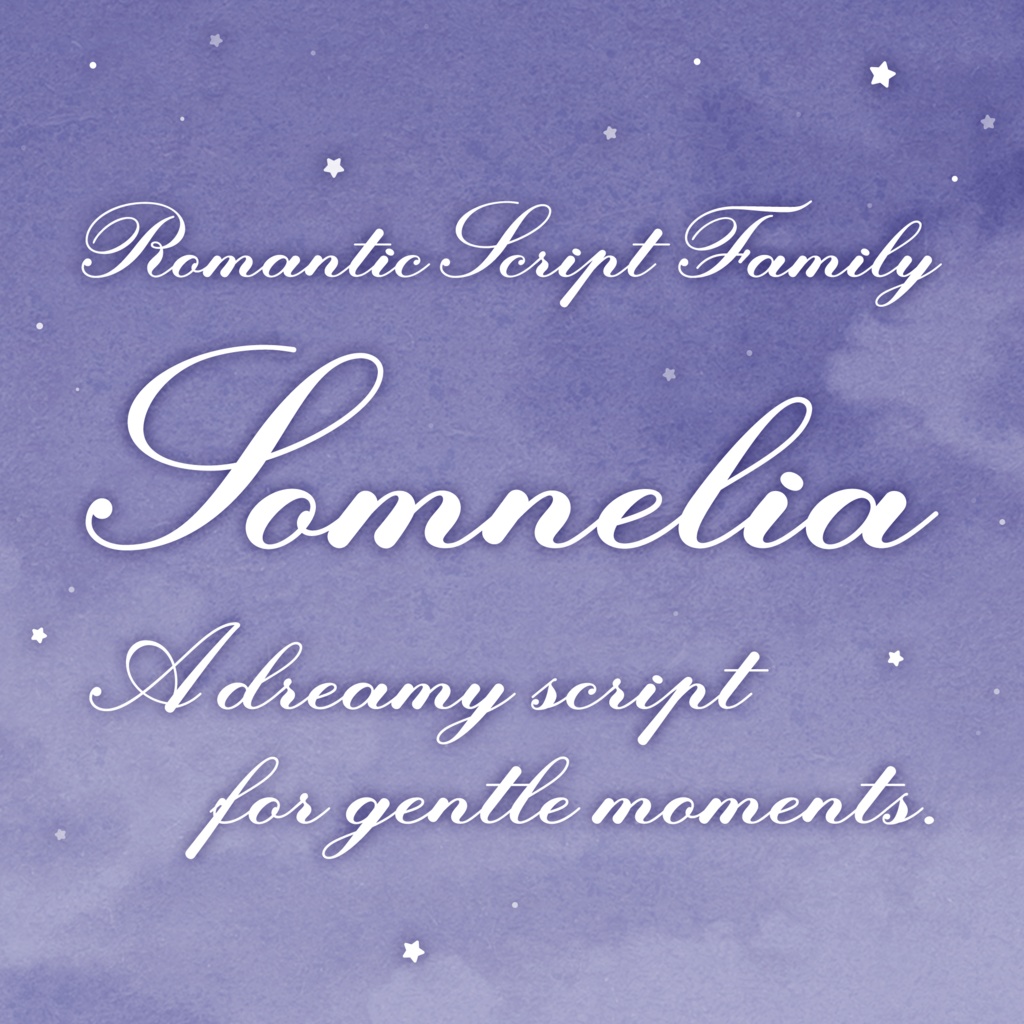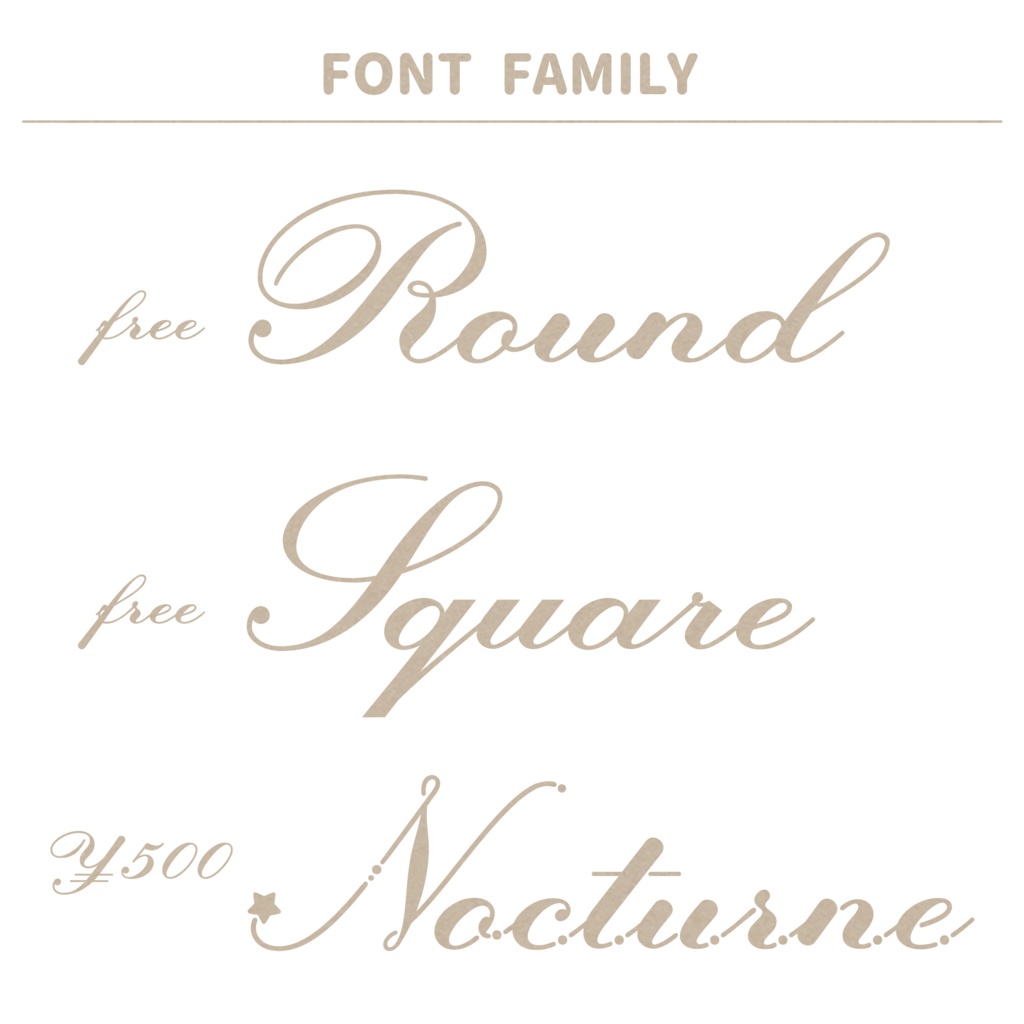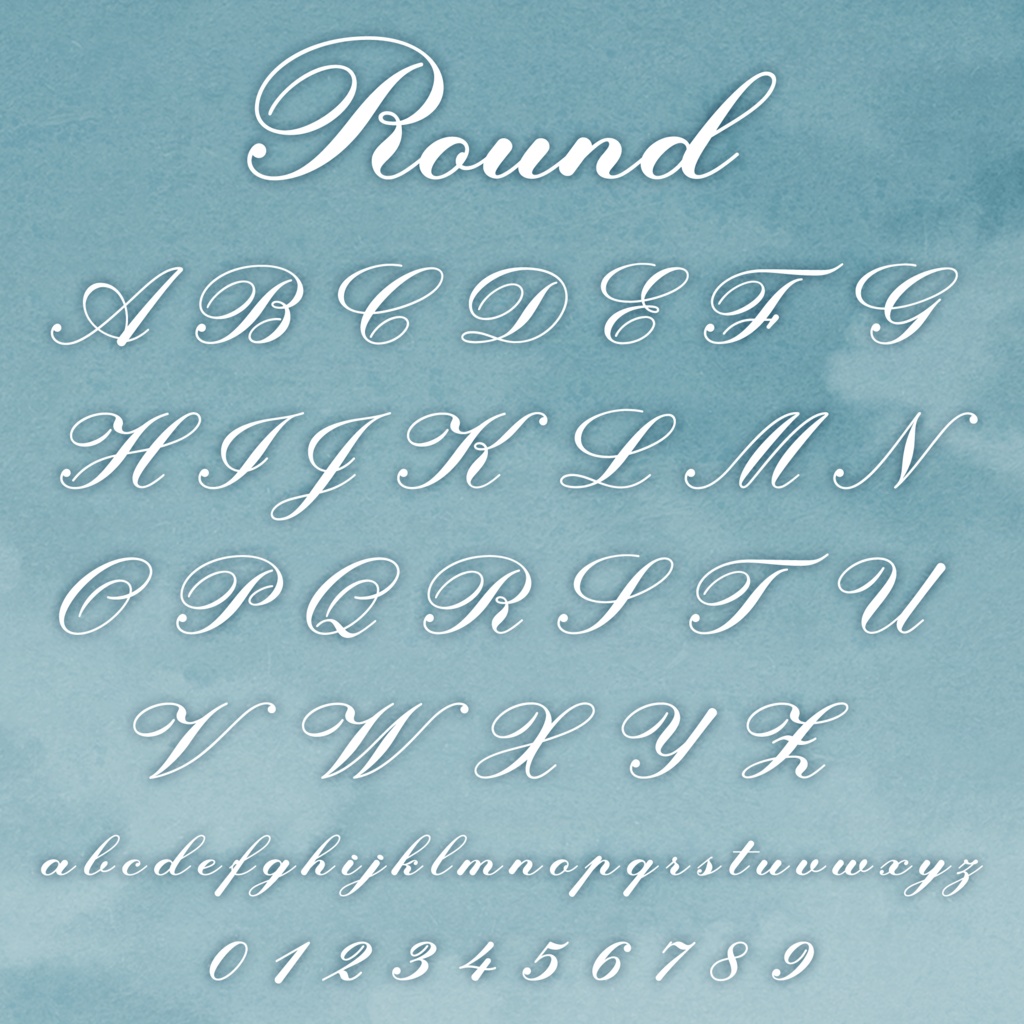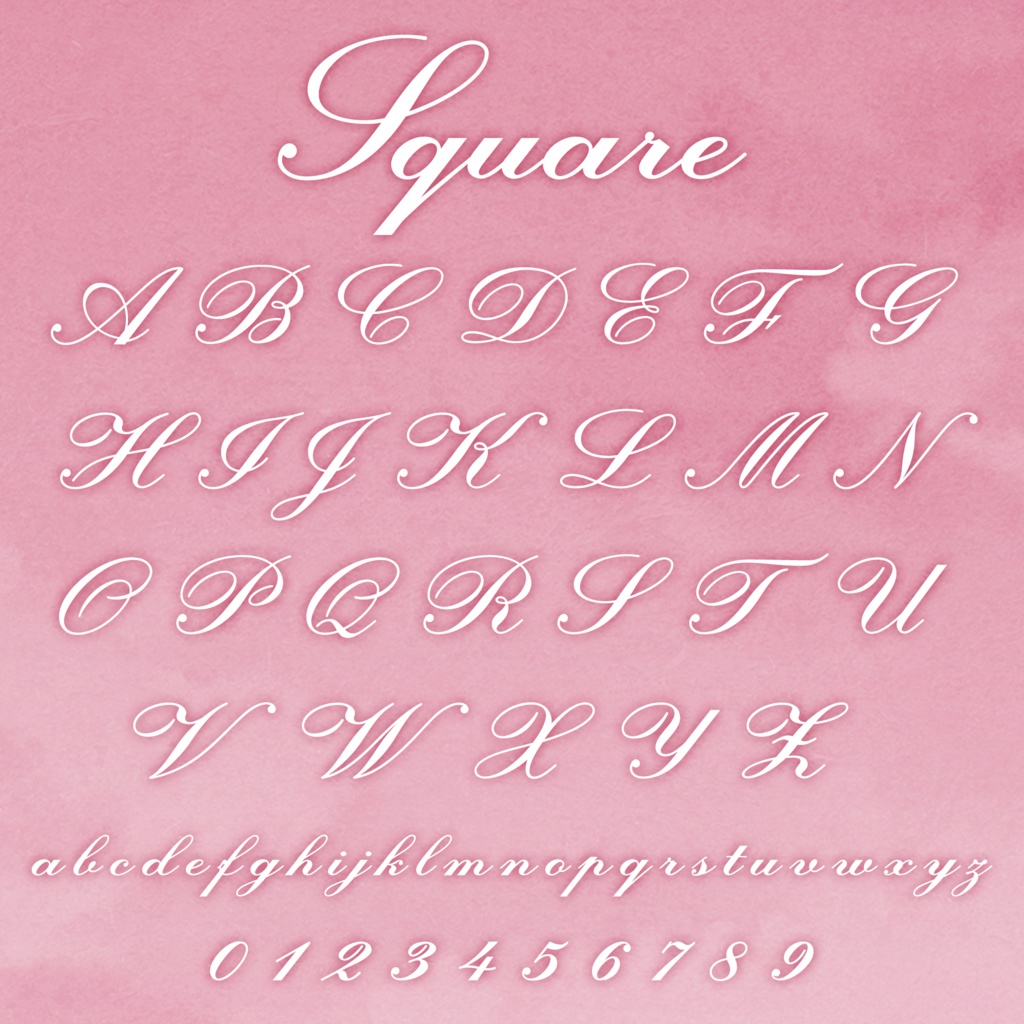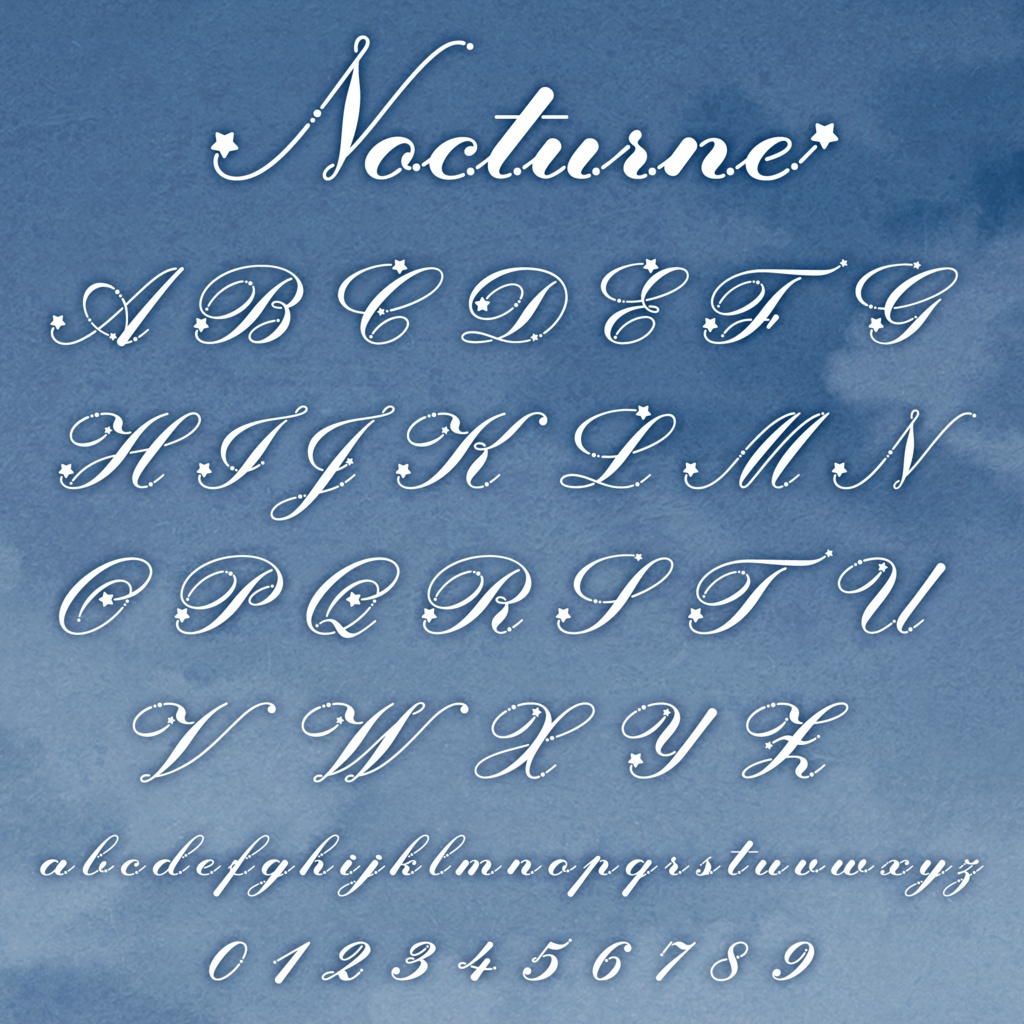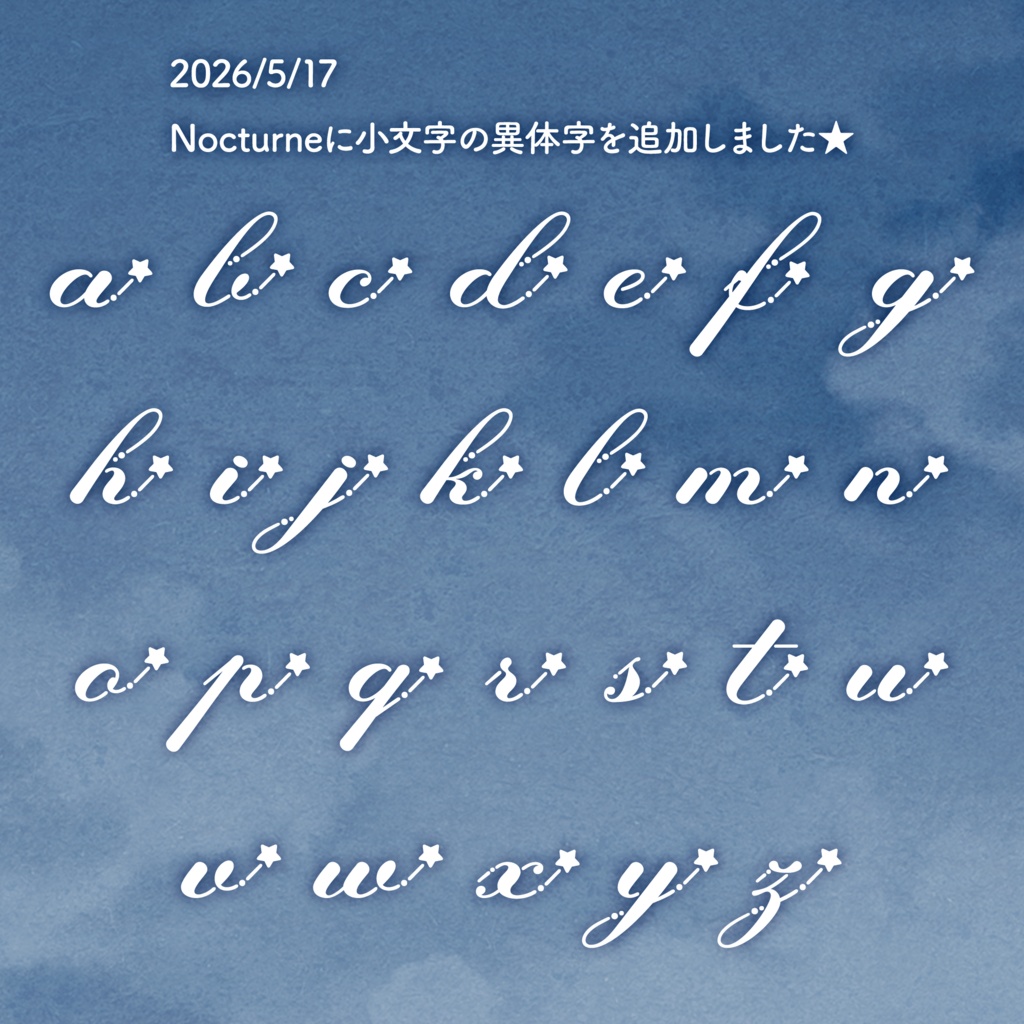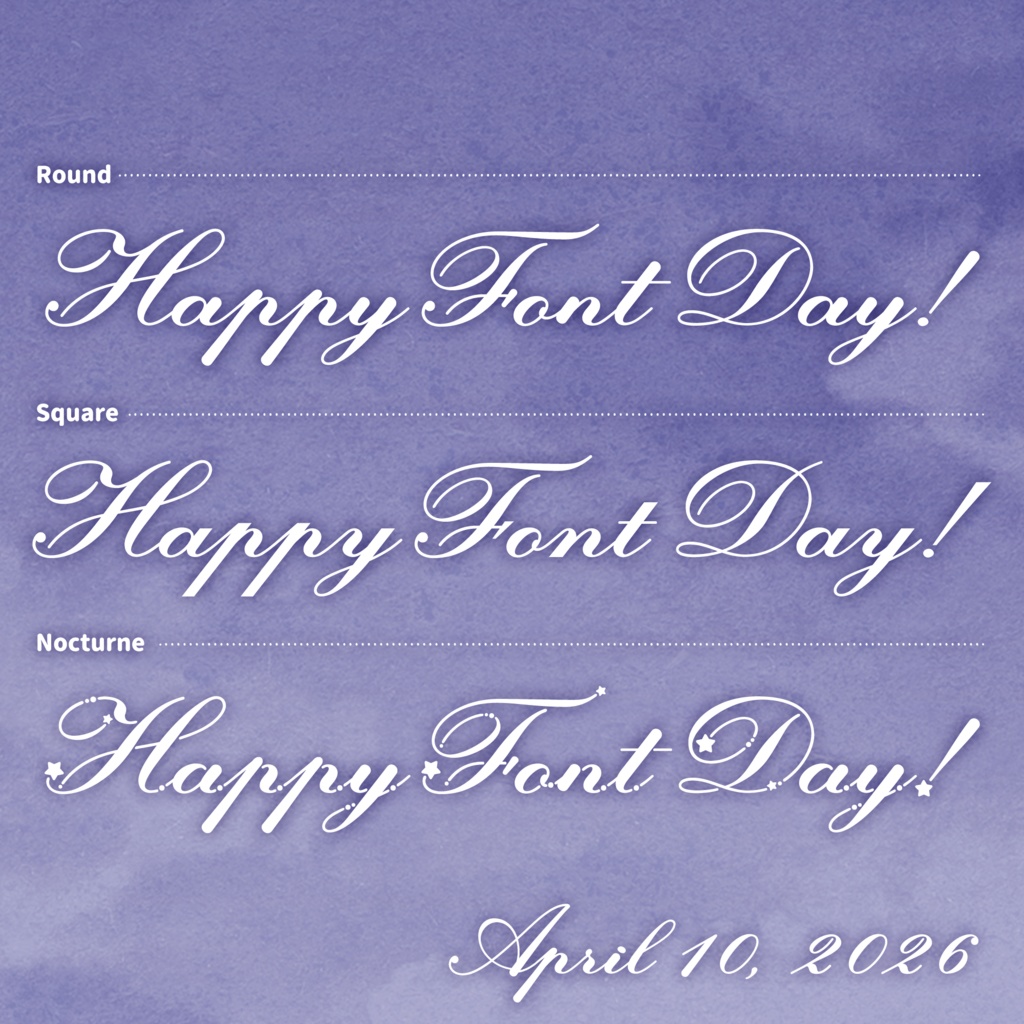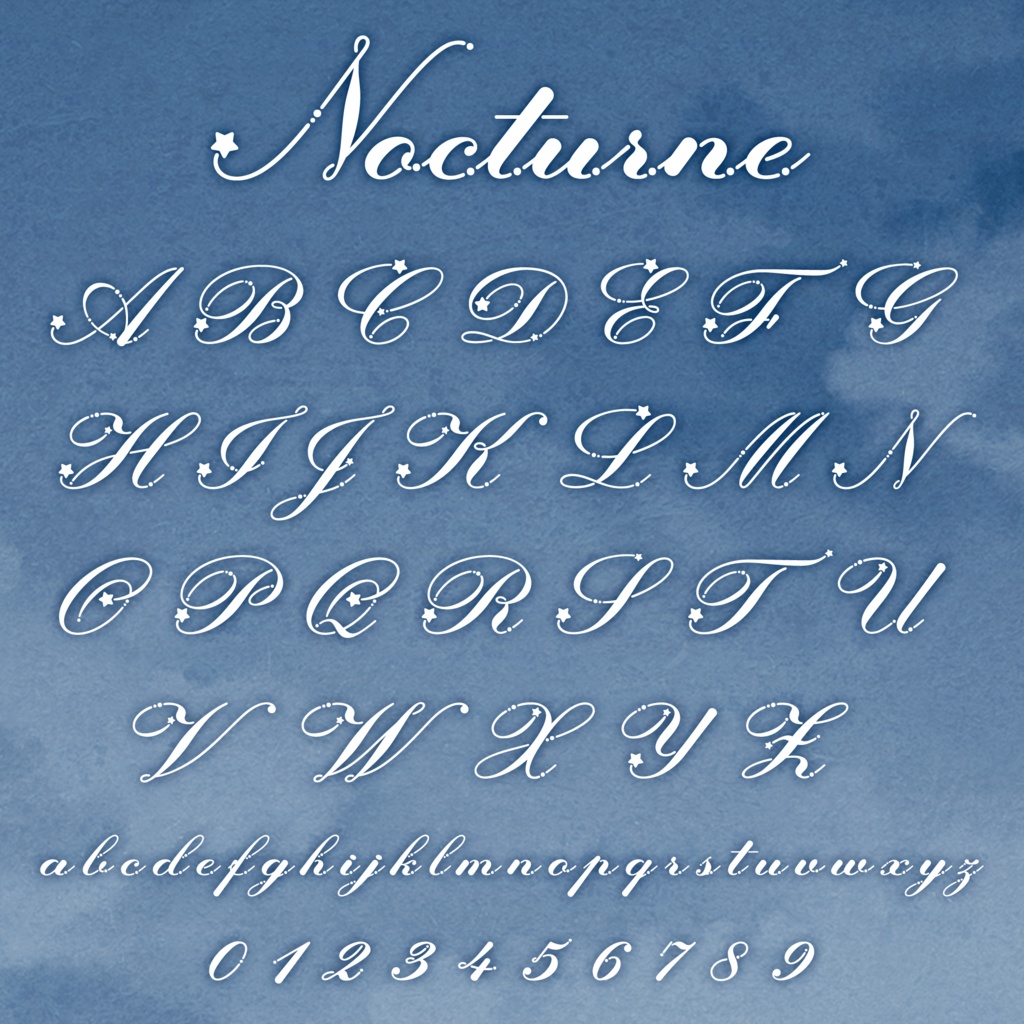
フォント「Somnelia」
Somneliaは、ふんわりとしたやわらかさと クラシカルな雰囲気をあわせ持つスクリプトフォントファミリーです。 線の表情にほどよいメリハリがあり、 軽やかでありながら落ち着きのある印象に仕上がっています。 ◆フォントの仕様 ファイル形式:OpenType Font(.otf) 文字内容:英数字・記号 異体字:Nocturneに1種類あり 今後のアップデートで異体字を追加&値上げ予定です。 ◆収録ファミリー Round / Square / Nocturne 無料版にはRound・Squareを収録しています。 Nocturneは有料ファミリーです。 ◆フォント名について Somnelia (ソムネリア)は、 ラテン語で夢を意味する「Somnia」をベースに、 花や女性名を思わせる語尾“-elia”を重ねた造語です。 ★利用規約はこちら https://satsuyako.com/license-agreement/